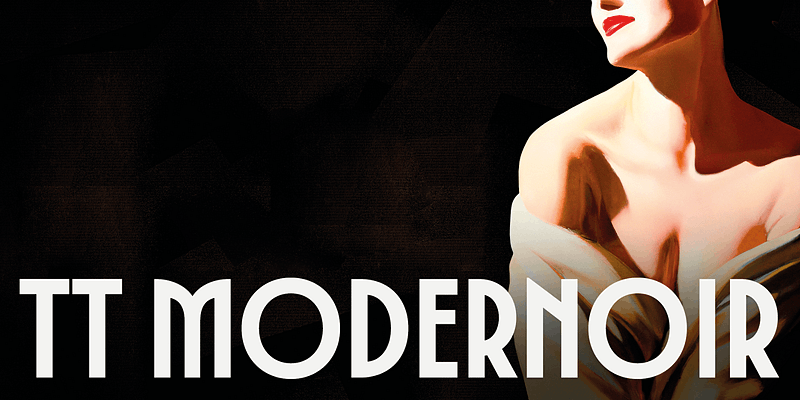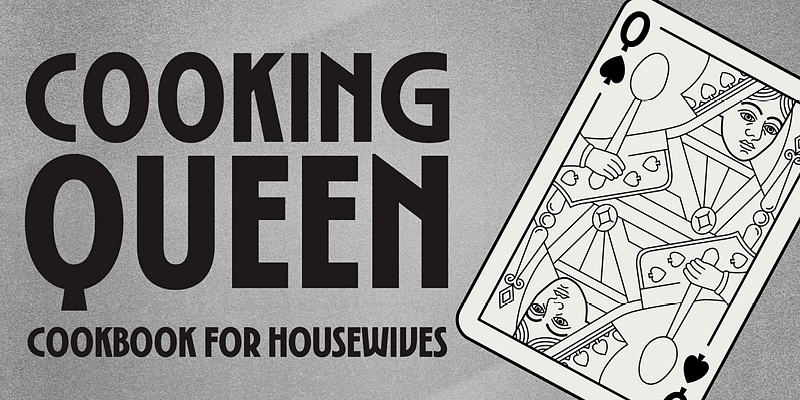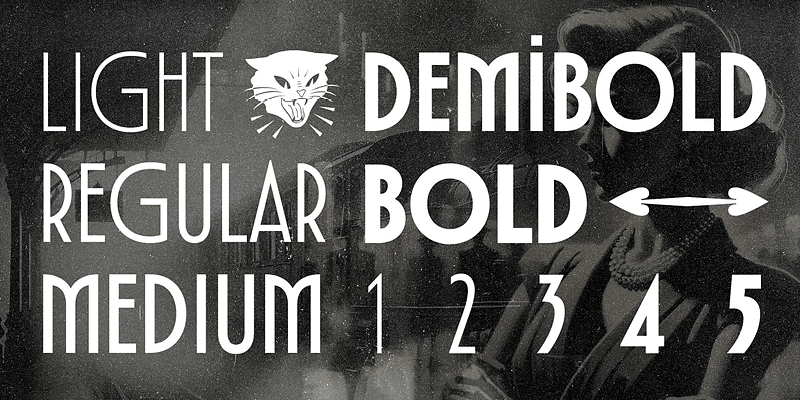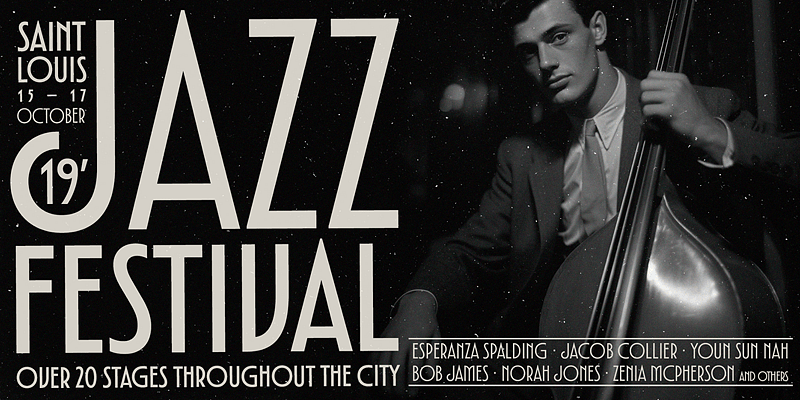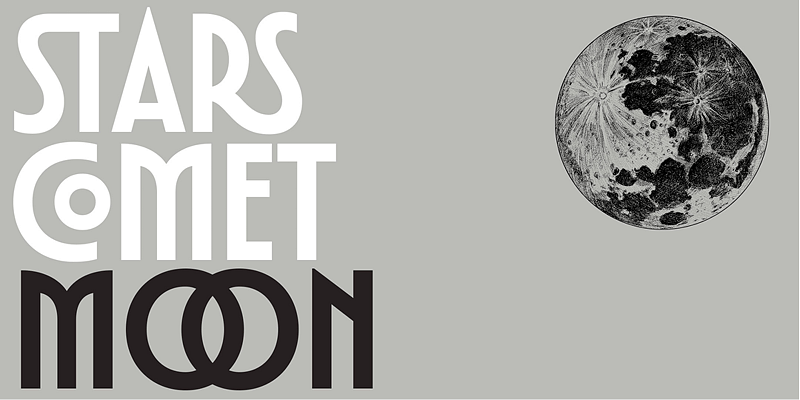
TT Modernoir es una tipografía para cartelería Sans Serif de dimensiones dinámicas. Las líneas fluidas y las delicadas formas estilo modernista de esta tipografía se combinan perfectamente con el flujo rítmico y la libertas improvisada del jazz. La principal característica de TT Modernoir es una diferencia marcada en la proporción de los caracteres cuadrados y ovalados. Las curvas en las piernas aportan a la fuente un aire exquisito, y las espirales dinámicas le aportan la sensación de ritmo y movimiento musicales.